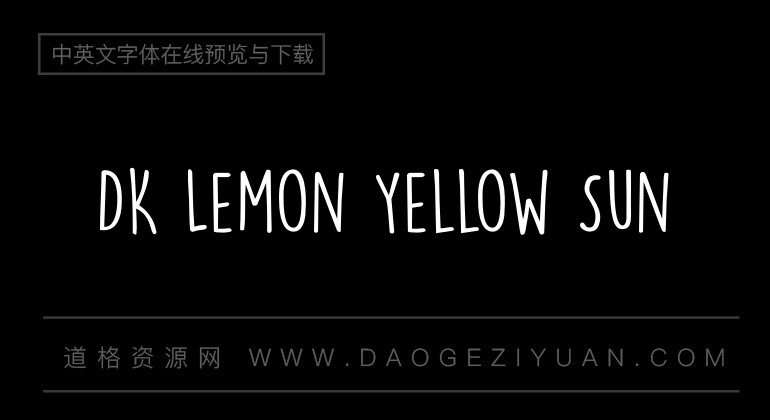
DK Lemon Yellow Sun 是一种非常流行的手写风格字体。它的风格非常有趣,具有很高的可读性和视觉吸引力。这种字体的特点是有点像手写的草书,但比草书更加整洁、清晰、漂亮。 DK Lemon Yellow Sun 字体由一位德国设计师Donis Miftahudin创建。该字体是由手写的草书风格慢慢演变而来的,因此具有很高的自然性和个性化。这种字体的字母有一些不规则的线条和形状,但整体上非常清晰,非常适合用于设计标语、海报、书籍封面、名片等多种场合。 DK Lemon Yellow Sun 字体也有很好的可扩展性,可以在不同大小和颜色的情况下使用。它提供了大写、小写字母、标点符号和数字,可以满足各种设计需求。如果您正在寻找一种具有个性化和手写感的字体,DK Lemon Yellow Sun 将是一个非常不错的选择。内容介绍
DK Lemon Yellow Sun是一款非常不错的手写艺术字体,具有很好的视觉感,适合于文化类的宣传设计、商业类品牌的广告和产品包装设计以及个性化文字排版等较多场景。